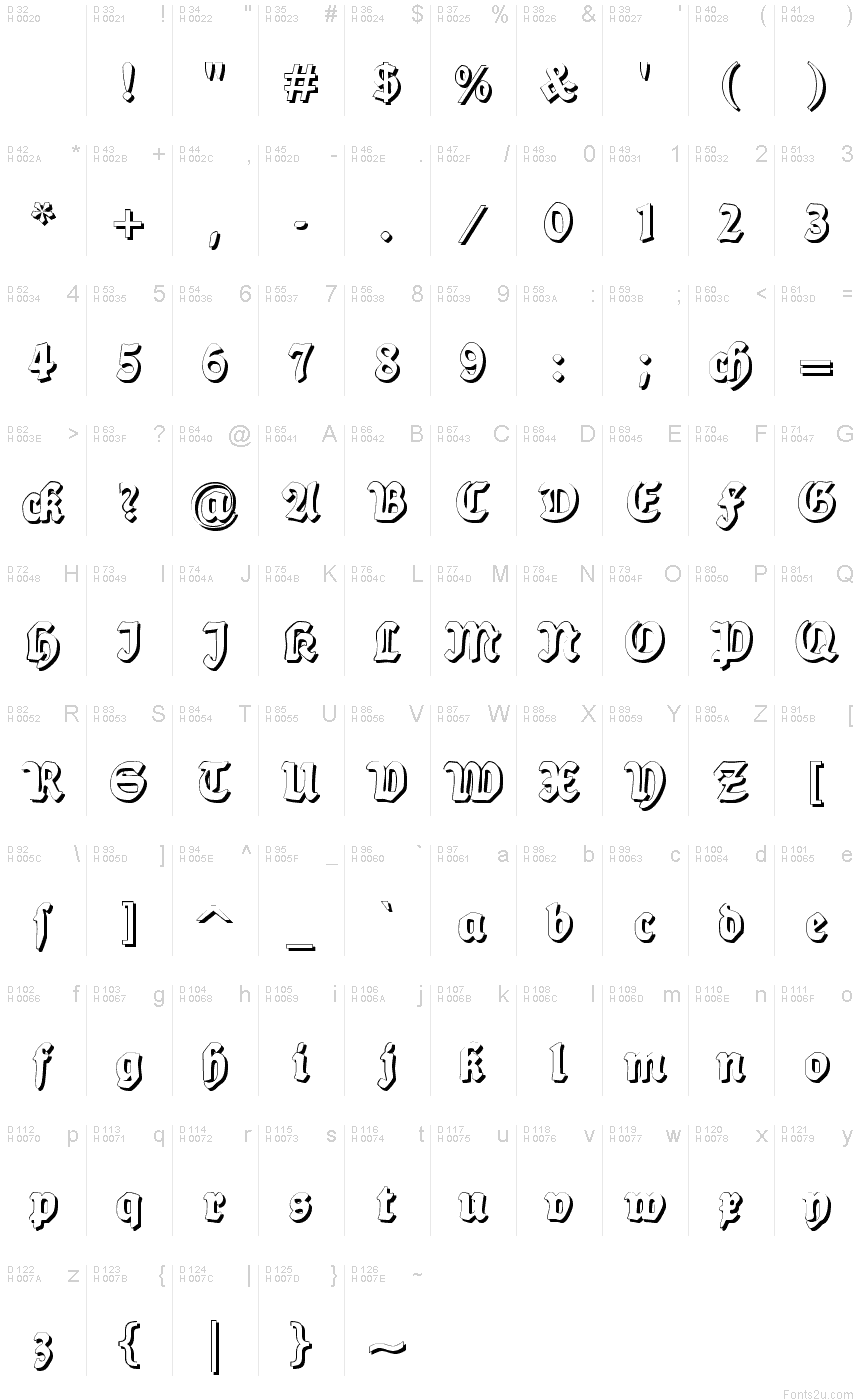
خط Ballade Shadow من تصميم Dieter Steffmann (Typographer Mediengestaltung) هو خط قوطي مجاني بطابع العصور الوسطى. تضفي أشكاله الجريئة ذات الطابع القوطي الأسود (blackletter)، ومنحنياته الغائرة، وخطوطه السميكة ظلاً داكناً ومزاحاً يذكرنا بيافطات الحانات القديمة المضاءة بضوء الشموع. تتراص الحروف بشكل متقارب لتخلق مظهراً صلباً ومحفوراً يضفي على التصاميم طابع الفانتازيا والفولكلور والتاريخ، مع الحفاظ على وضوح القراءة.
باستخدام خط Ballade Shadow، ستبرز العناوين على أغلفة روايات الفانتازيا، وعناوين الألعاب، وملصقات المشروبات، ومنشورات المهرجانات، وقوائم الطعام ذات الطابع التاريخي، وشعارات الفرق الموسيقية. يتألق هذا الخط المجاني عند استخدامه بأحجام كبيرة حيث يمكن لظله الحبري أن يبرز بوضوح؛ قم بإقرانه بوزن عادي من عائلة Ballade أو بخط هندسي بسيط بلا زوائد (sans serif) للحفاظ على نصوص الدعم واضحة وعصرية.